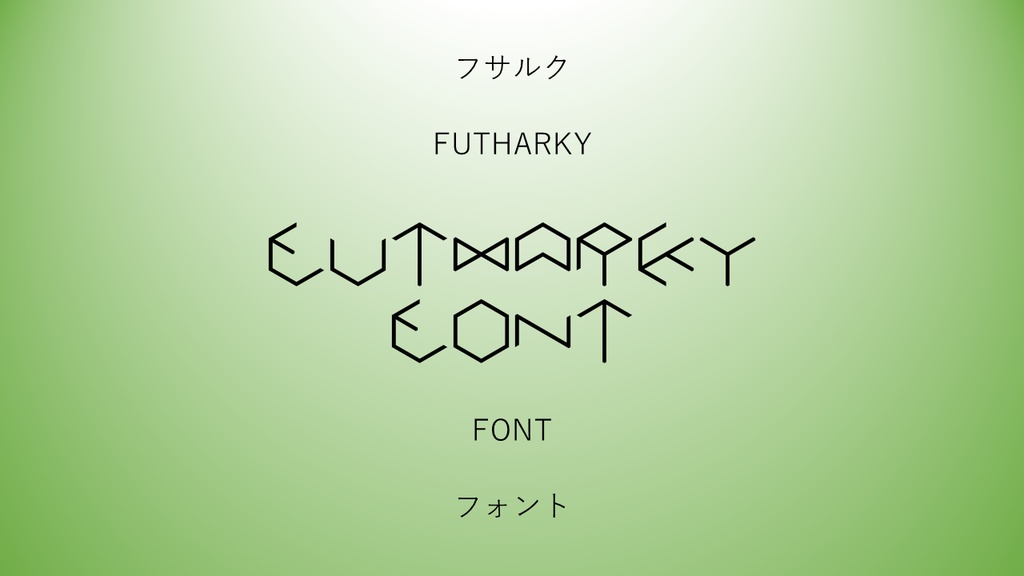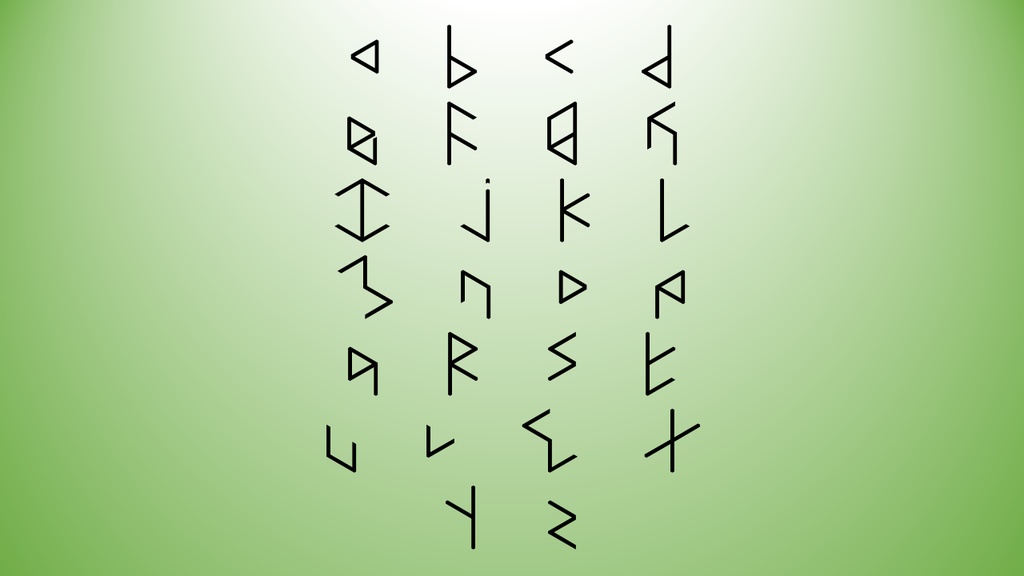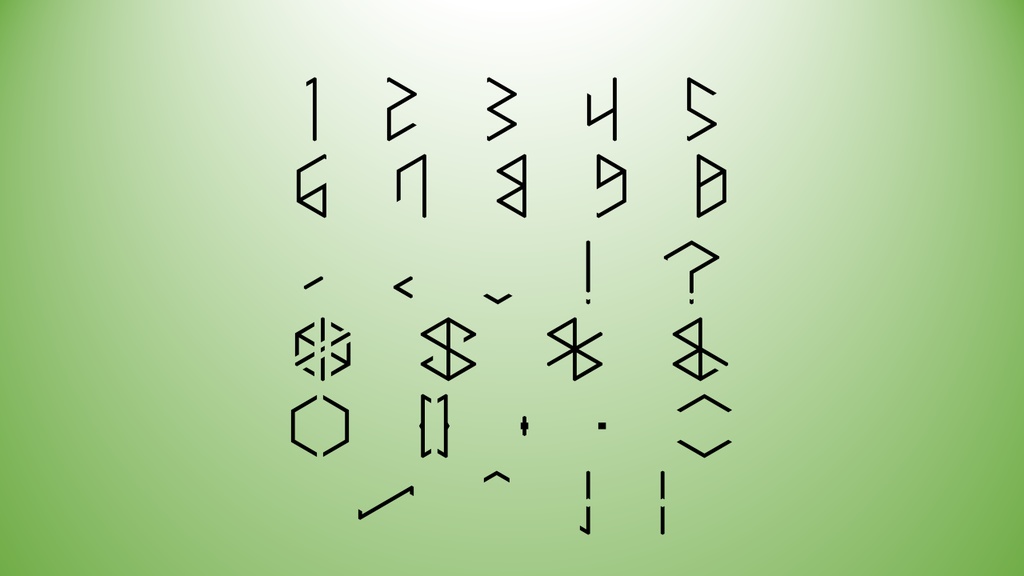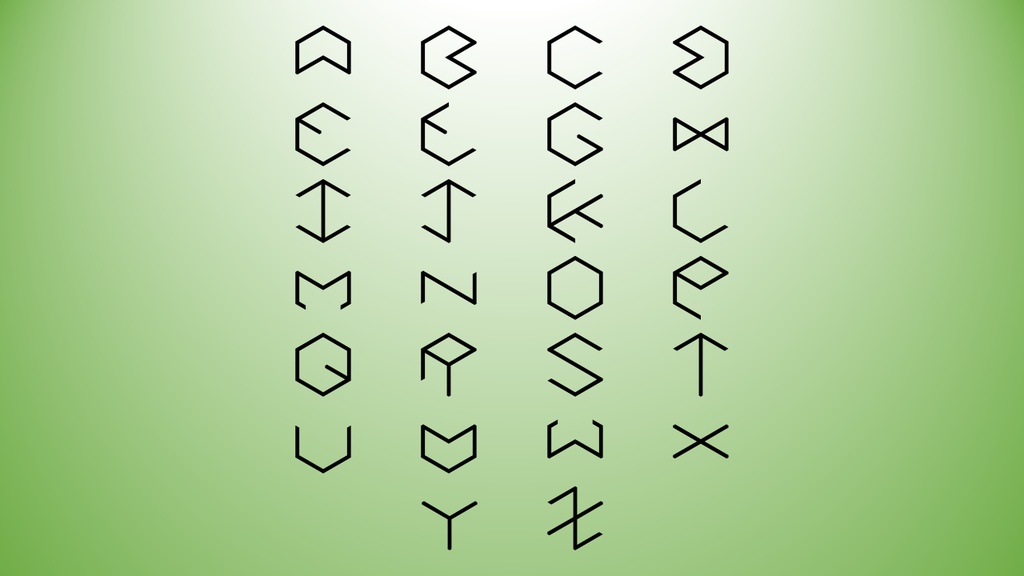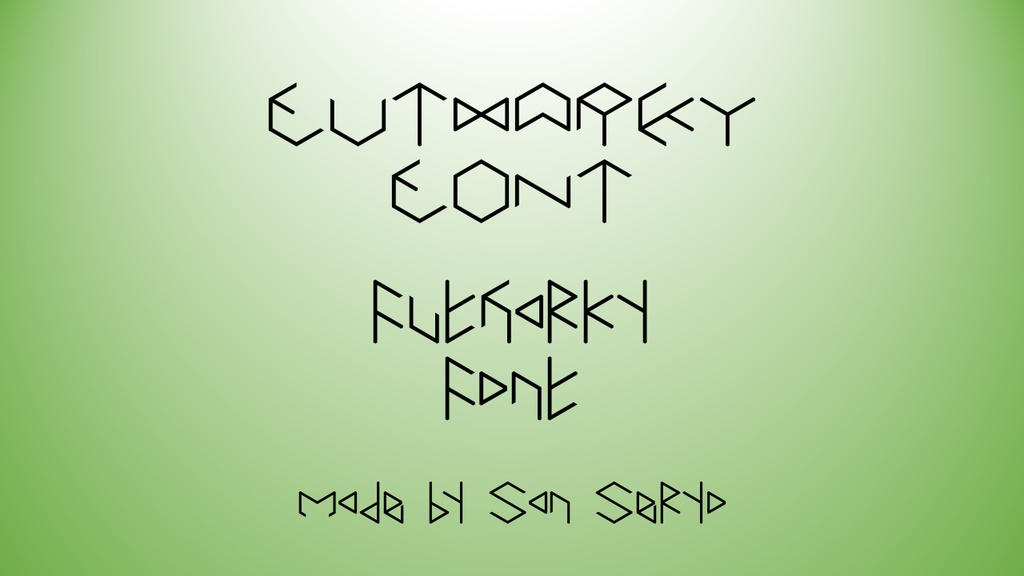
Futharky_Font
ルーン文字(フサルク)からインスピレーションを得たフォントです。 可読性は低いため、食器や服飾のデザインなどにお使いください。 文字はA~Zまでの大文字および小文字、数字、記号となっております(画像参照)。 Windows 、Mac それぞれに対応している OpenType および TrueType の Futharky_Font を同梱しております。 ただし、WindowsにおけるOpenTypeしか動作確認をしておりません。 もし不具合などございましたら、お手数ですがご連絡のほどよろしくお願いいたします。 順次、不具合などを修正して更新していく予定です。 このフォントは芹生彡が作製したものであり、著作権は放棄していません。 購入後は複数のプロジェクトに亘って使用可能です。 ご利用に関して当方へ連絡する必要はありませんが、成果物などについてご一報くださると今後の活動の励みになります。 以下の規約の基、ご自由にお使いください。 ▼商用利用可能 ▼自作発言および作者の虚偽の禁止 ▼再配布禁止 ▼アダルトサイト、アダルトゲームでの使用は原則禁止(どうしてもという場合はご相談ください) ▼政治活動での利用を禁ずる ▼犯罪に抵触する可能性のある行為に利用することを禁ずる ▼利用する場合、当該作品内もしくは作品概要欄等にクレジットを明記ください 例:フォント/芹生彡 本フォントを使用したこと、本ファイルをダウンロードしたことにより起こった事象については責任を負いかねますので、ご利用は自己責任でお願いします。 本規約は予告なく変更される場合があります。予めご了承お願いします。 This font is inspired by the rune script (Futhark). Legibility is low, so use it for tableware and clothing designs. The characters are in upper and lower case from A to Z, numbers and symbols (see image). Futharky_Fonts are included for both Windows and Mac, and are compatible with both OpenType and TrueType fonts. However, I have only confirmed the operation of OpenType on Windows. If you have any problems, please contact us. We plan to fix the bugs and other issues as they arise and update the site. This font was created by Serio and we have not waived our copyright. Once purchased, you may use it across multiple projects. You do not need to contact us about your use, but you may let us know about your work, etc., to encourage us to do so in the future. Please feel free to use it under the following terms. ▼Available for commercial use. ▼Prohibits self-made statements and falsehoods of the author ▼Redistribution prohibited ▼In principle, use of adult sites and games is prohibited (Negotiable). ▼Forbidden to use it for political activities. ▼Prohibits the use of such a device to commit an act that may violate a crime. ▼If you use the work, please credit it in the work or in the summary section of the work. Example: Font/Seryo San. We are not responsible for the use of this font or for any problems that may occur as a result of downloading this file. Please note that the terms of use are subject to change without notice. Please note that they are subject to change without notice.